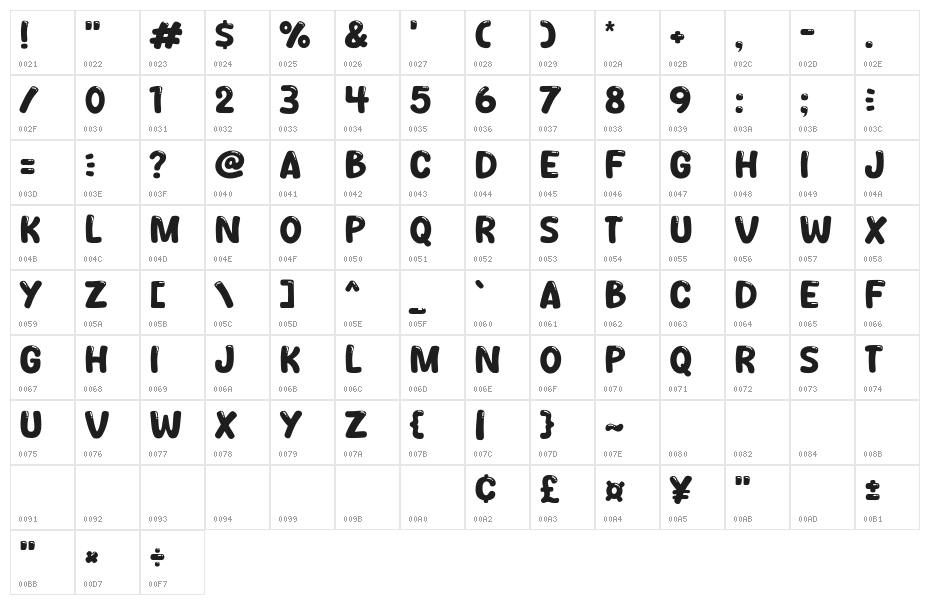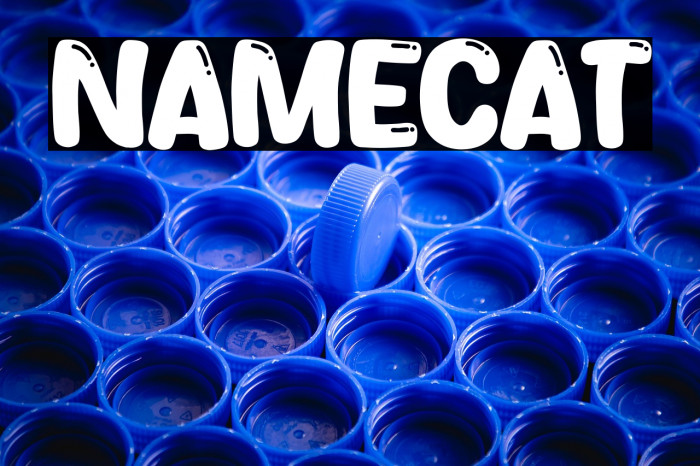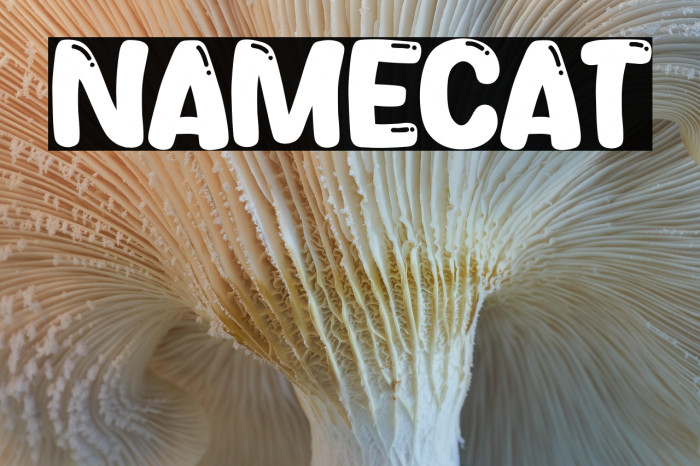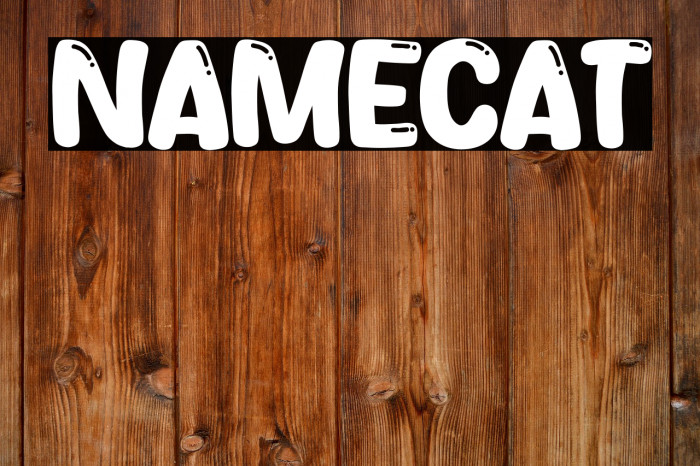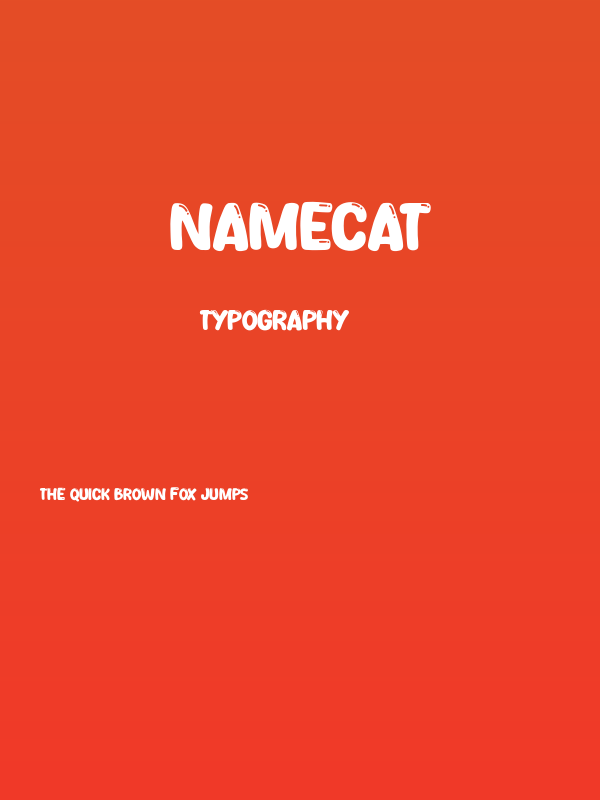
Namecat Font
| 整体风格 | Playful, Cartoonish, Fun |
| 使用场景 | Headlines, Logos, Posters, Children's materials |
| 推荐项目 | Children's books, playful branding, party invitations, comic strips, and educational materials. |